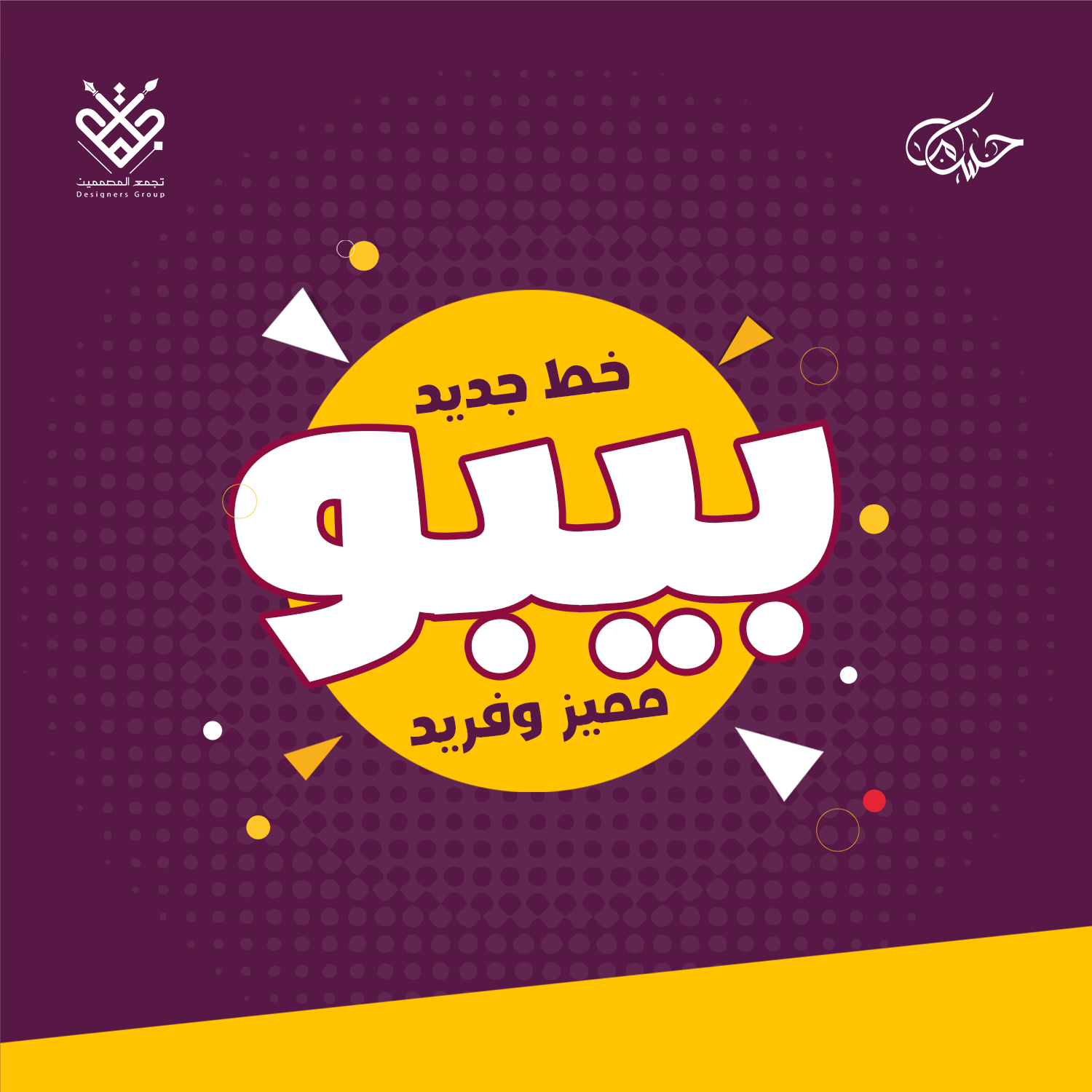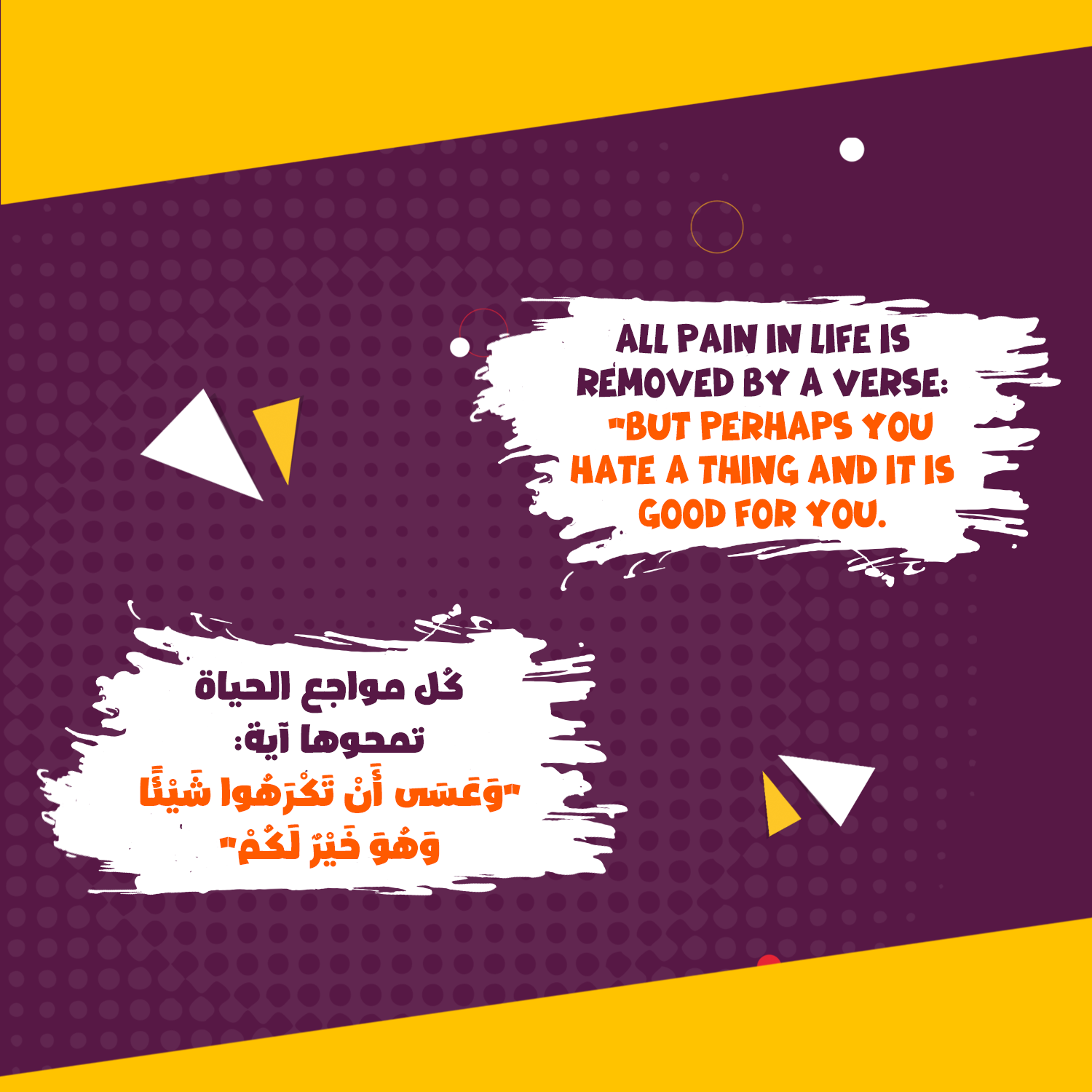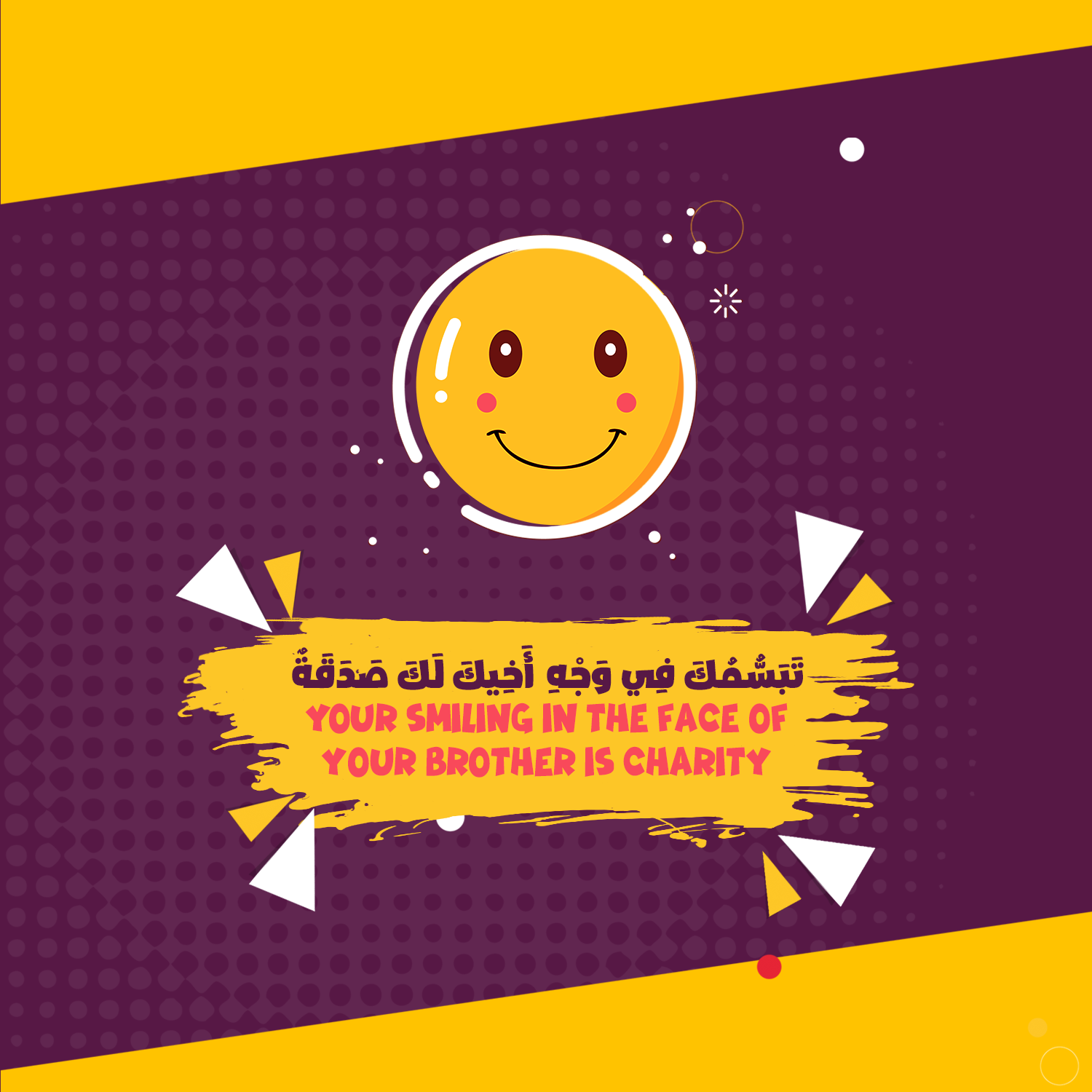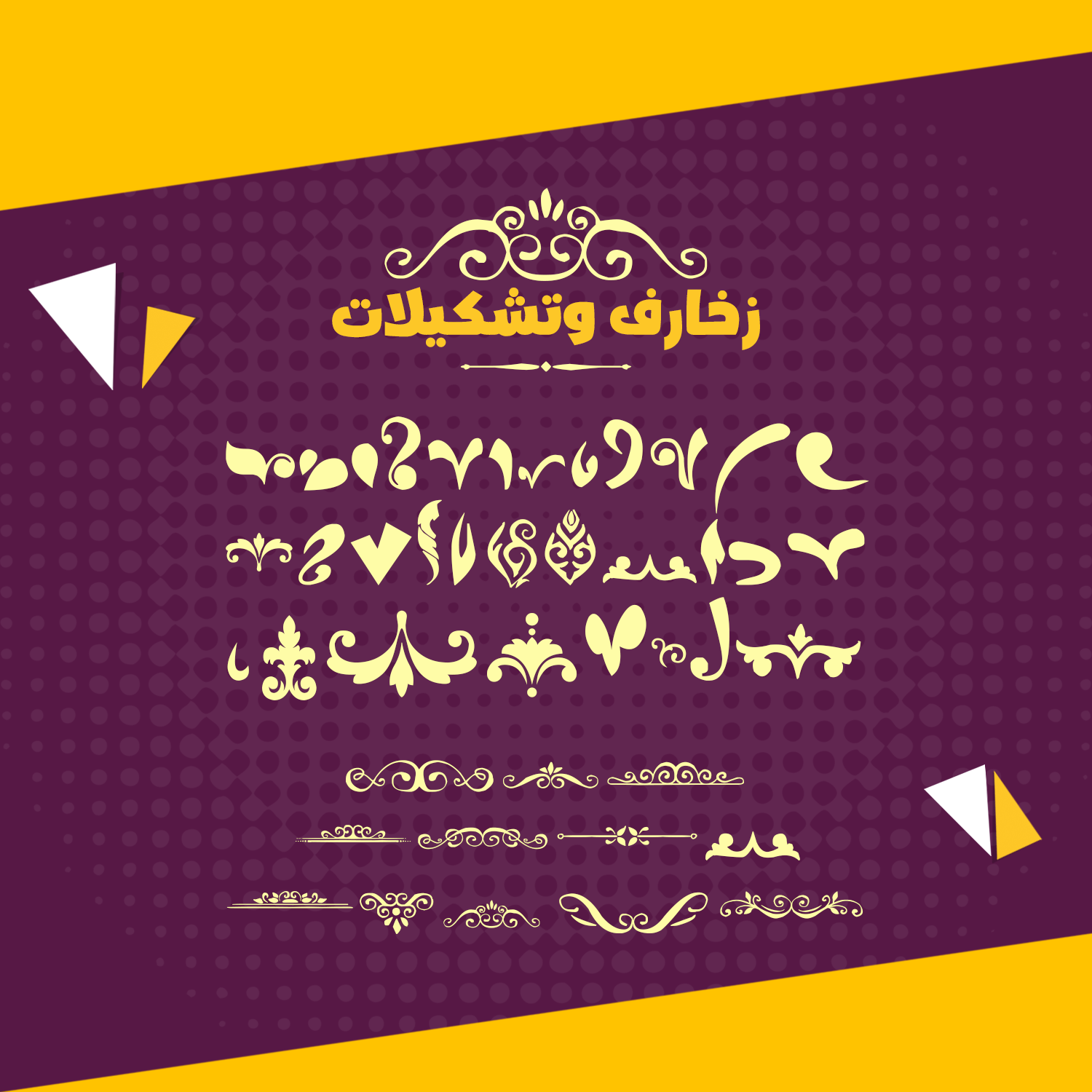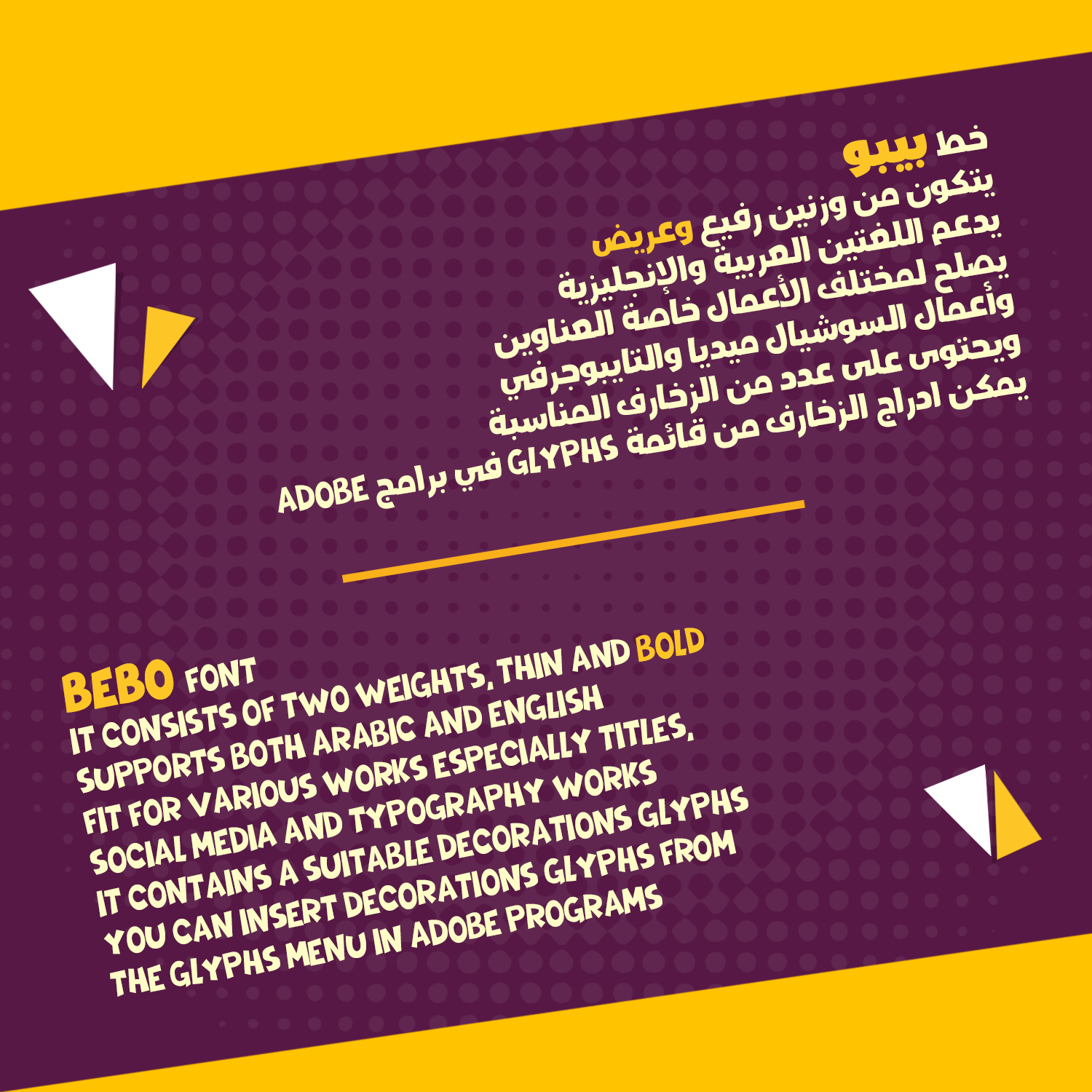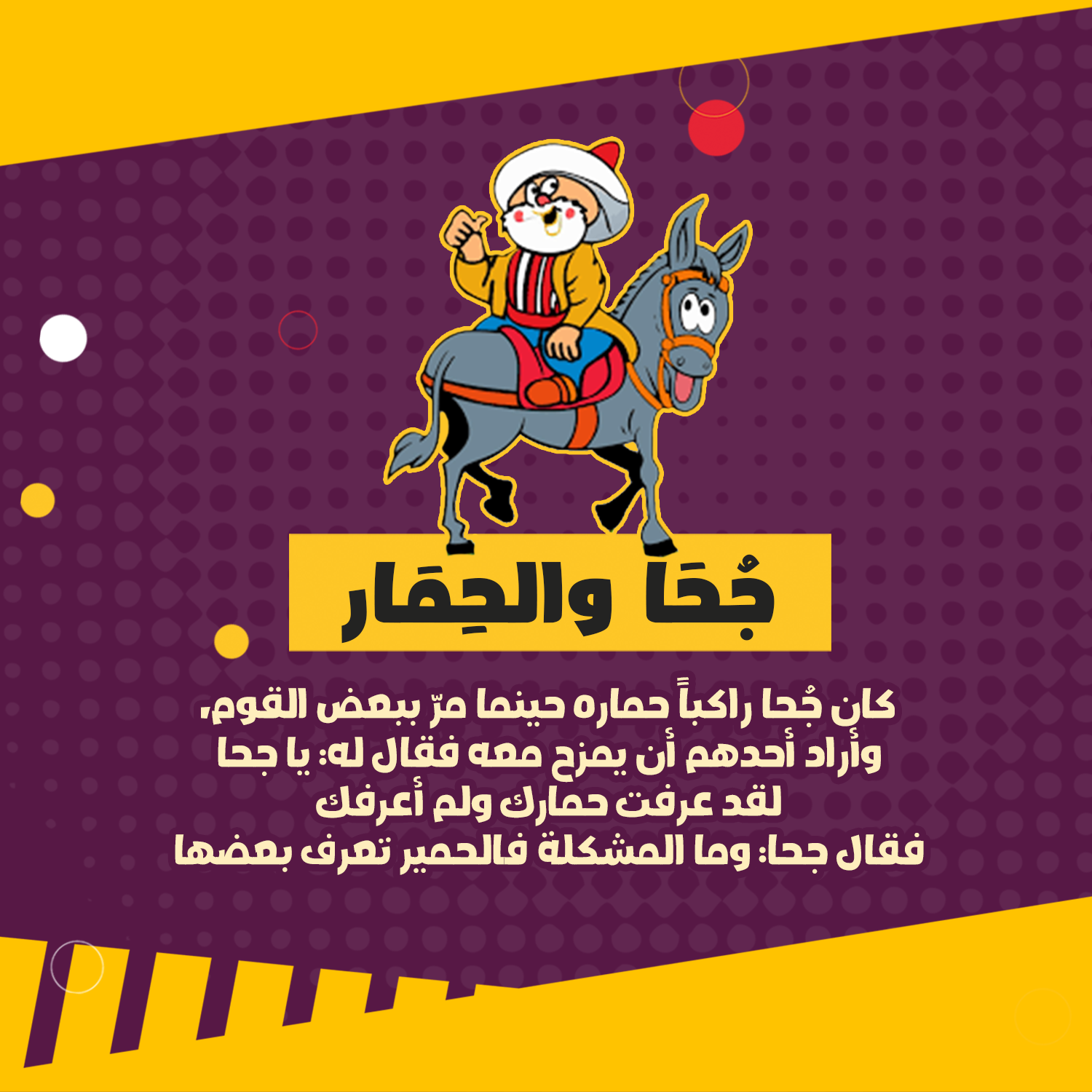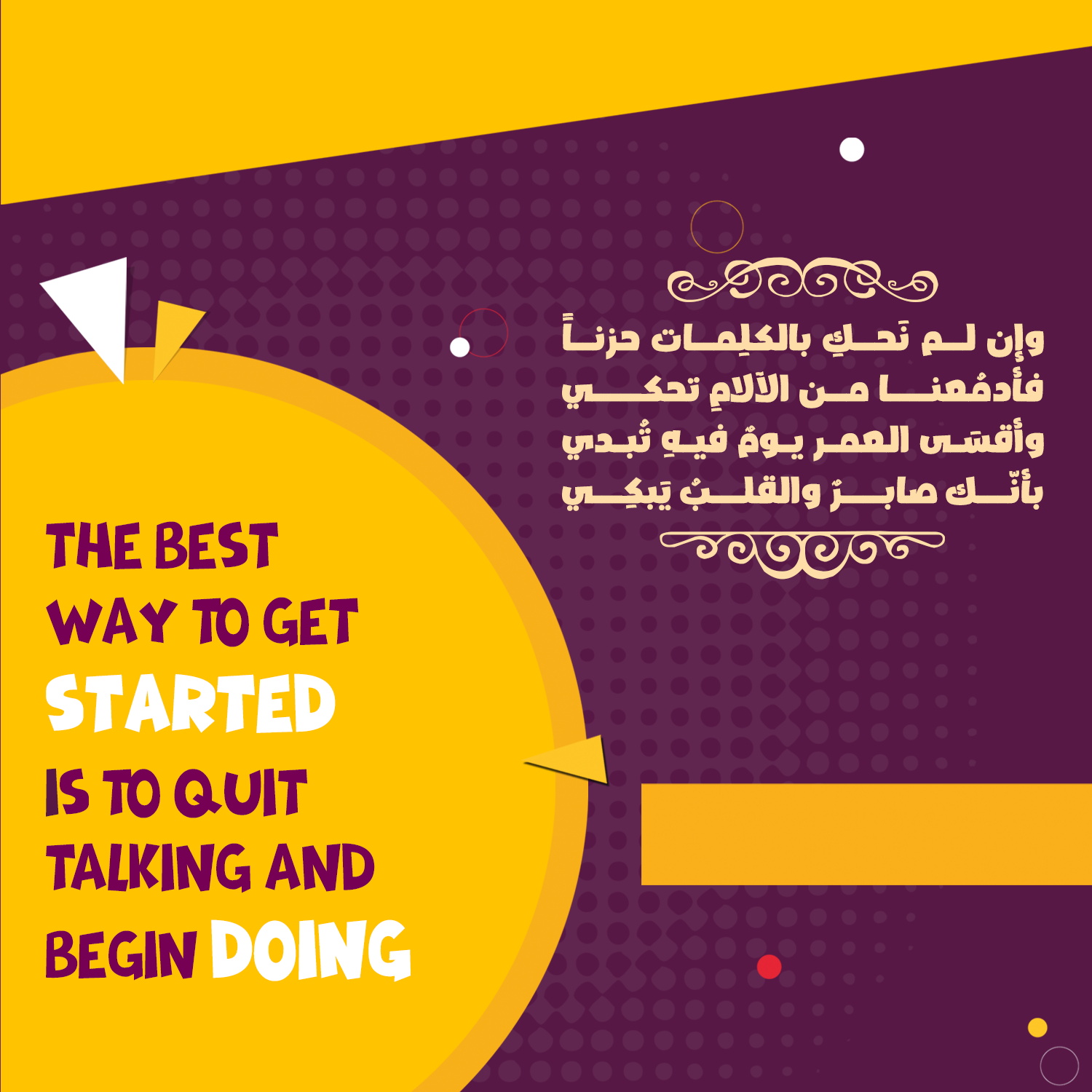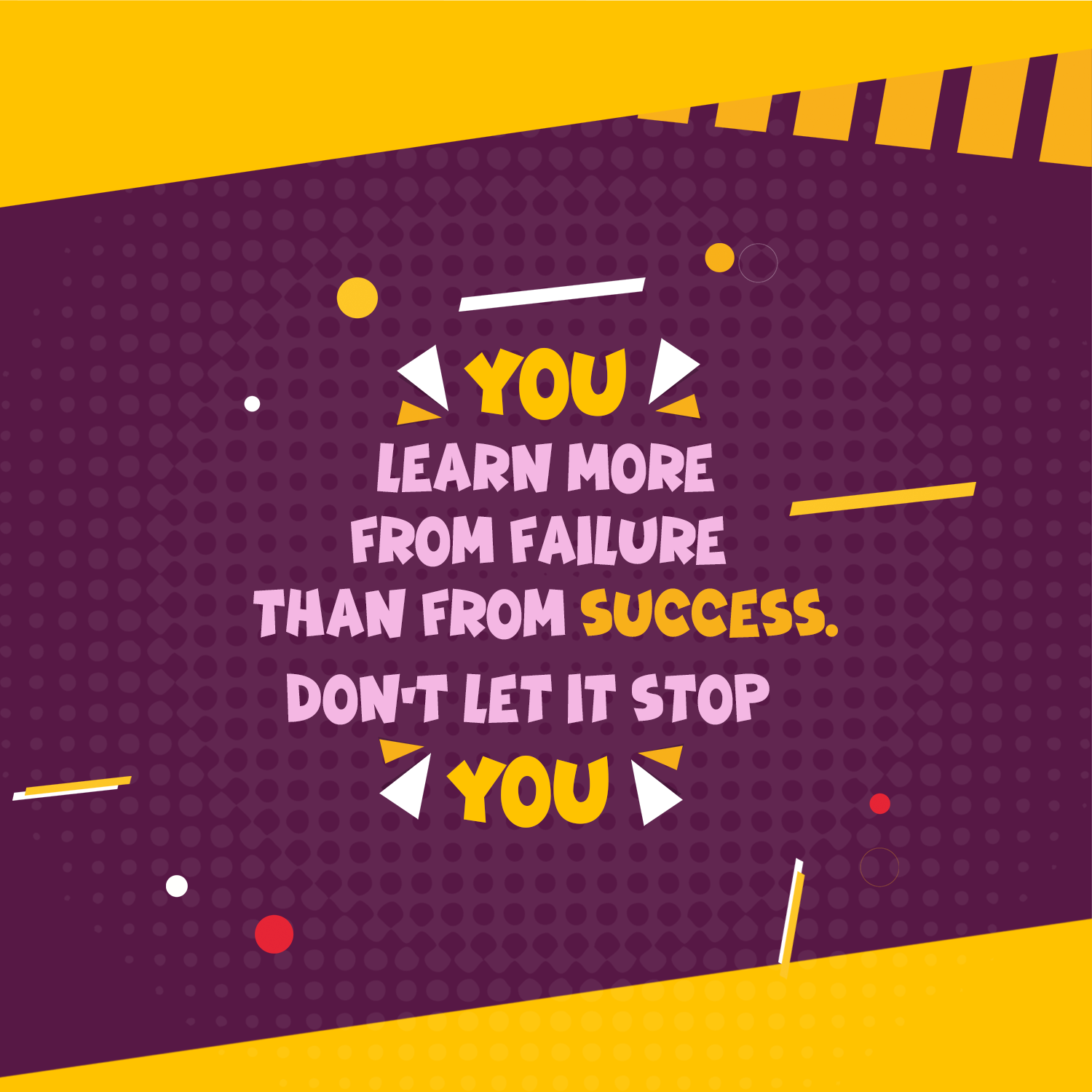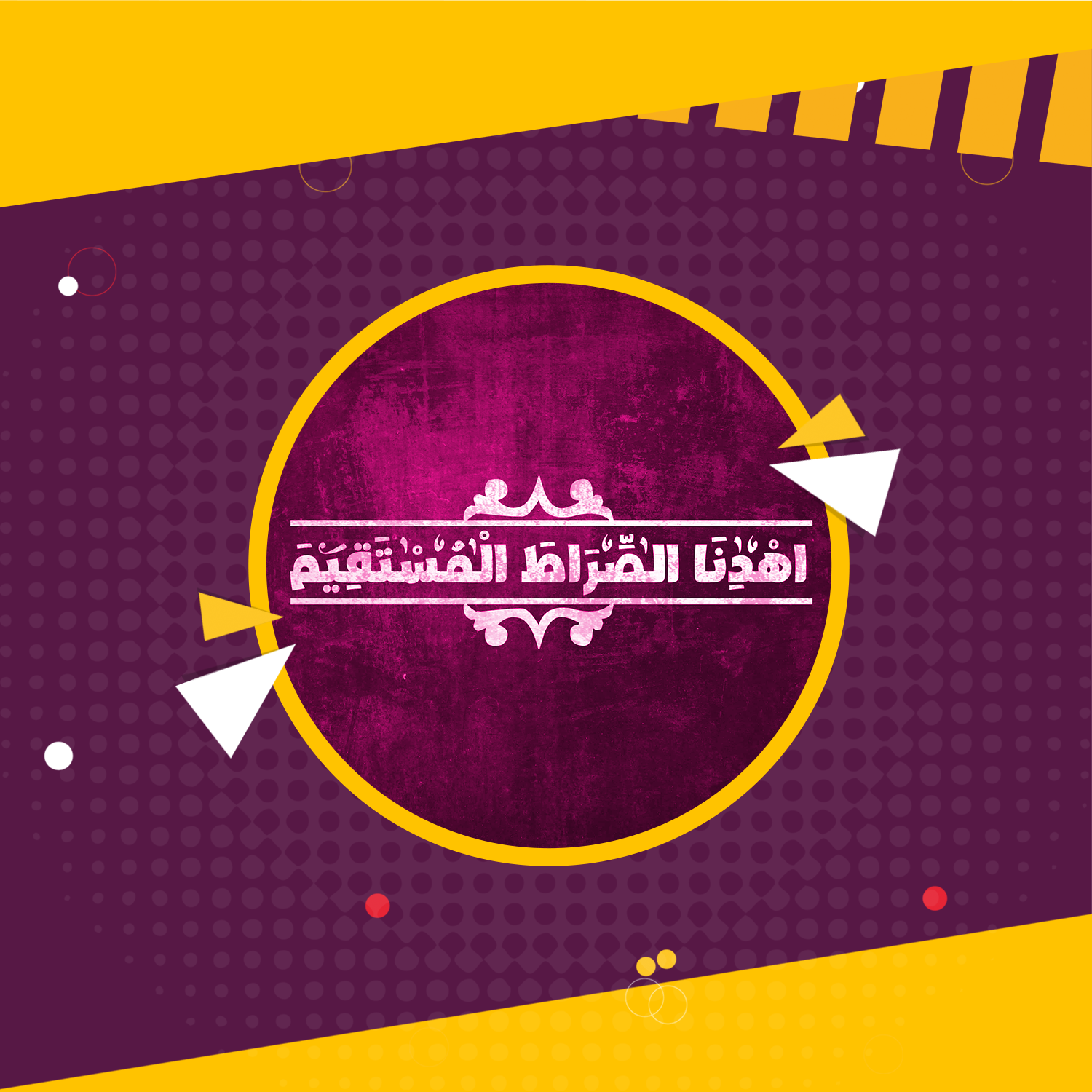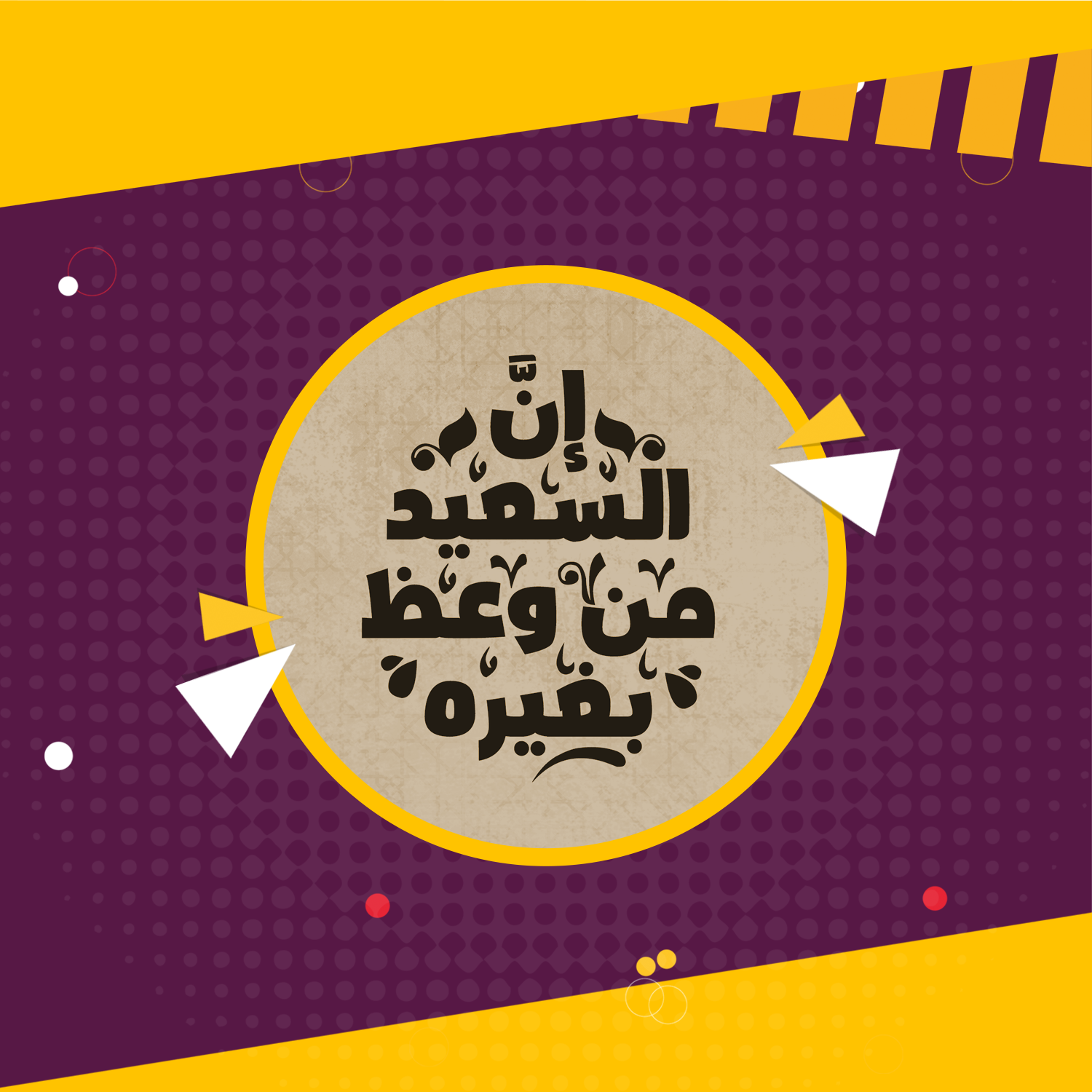
بيبو خط  يتكون من وزنين رفيع وعريض يدعم اللغتين العربية والإنجليزية يصلح لمختلف الأعمال خاصة العناوين وأعمال السوشيال ميديا والتايبوجرفي ويحتوى على عدد من الزخارف المناسبة يمكن ادراج الزخارف من قائمة المحارف  في برامج أدوبي
Bebo font is consists of two weights, thin and bold Supports both Arabic and English Fit for various works especially titles, social media and typography works it contains a suitable decorations glyphs you can insert decorations glyphs from the Glyphs menu in Adobe programs